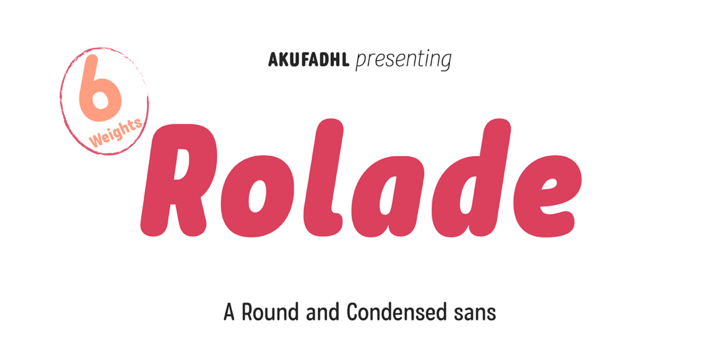
Descubra a beleza da modernidade com o Rolade Font Family, uma fonte sans-serif desenvolvida pelo designer Hamilton para uso em destaque. Composta por elementos redondos e condensados, ela traz um charme único e divertido, perfeitamente adaptada para aplicações visuais exigentes. Primeiramente concebida como tipo aberto em 2015 baseado num projeto pessoal, o Rolade se transformou com alternativas que oferecem uma variedade de personalização. Suportando uma gama completa de línguas basadas no latim, este é um recurso gráfico perfeito para tornar seu design mais atraente e versátil.